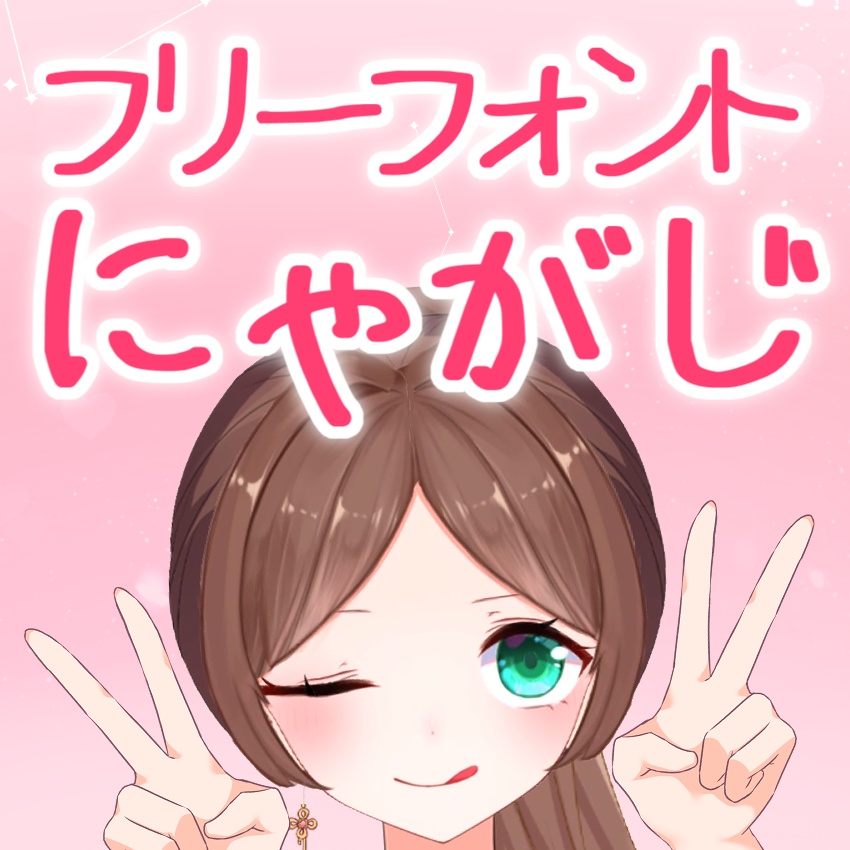
星星店【フリーフォント】にゃがじDigital0 JPY무료 다운로드にゃがじ.zip (1.63MB)にゃがじ.zipAbout Gift字下手Vtuber 星娘が配信で作成した手書きフォントです 対応文字は JIS第一水準漢字までで JIS第二,第三水準も一部含まれます 個人・商用とも無償で自由に使用することができます星星店Visit FANBOX!Materials (Other)【フリー素材】画像認証サムネテンプレート【Vtuber向け】星星店0 JPYFonts【Aviutl】字幕/テロップ用エイリアスF星星店0 JPYFonts【Aviutl】字幕/テロップ用エイリアスE星星店0 JPYFonts【Aviutl】字幕/テロップ用エイリアスD星星店0 JPYFonts【Aviutl】字幕/テロップ用エイリアスC星星店0 JPYFonts【Aviutl】字幕/テロップ用エイリアスB星星店0 JPYFonts【Aviutl】字幕/テロップ用エイリアスA星星店0 JPYMaterials (Other)【フリー素材】VTUBERTCHI【Vtuber向け】星星店0 JPYMaterials (Other)【フリー素材】リスナーの反応テンプレート【Vtuber向け】星星店0 JPYMaterials (Other)【フリー素材】選挙特番プロフィール【Vtuber向け】星星店0 JPYMaterials (Other)【フリー素材】私の年収低すぎテンプレート【Vtuber向け】星星店0 JPYPlushiesOut of StockNIAGA TRACKSUITS BEAR MASCOT星星店1,400 JPYGoods (Other)Out of StockNIAGA HEBI MAGNET星星店800 JPYAcrylic KeychainsOut of StockNIAGACRYLIC keychain + NFC (MINGNIANG)星星店1,000 JPYAcrylic KeychainsOut of StockNIAGACRYLIC keychain + NFC (XINGNIANG)星星店1,000 JPYPlushiesOut of Stock【再販】NIAGA MOCHIMOCHI MASCOT星星店1,200 JPYMaterials (Other)【フリー素材】REACH【Vtuber向け】星星店0 JPYMaterials (Other)【フリー素材】サムネに使えるルーレット枠【Vtuber向け】星星店0 JPYMaterials (Other)【フリー素材】ガーリーな私服5着【Vtuber向け】星星店0 JPYGoods (Other)NIAGA PINGHE CHARM星星店800 JPY더보기